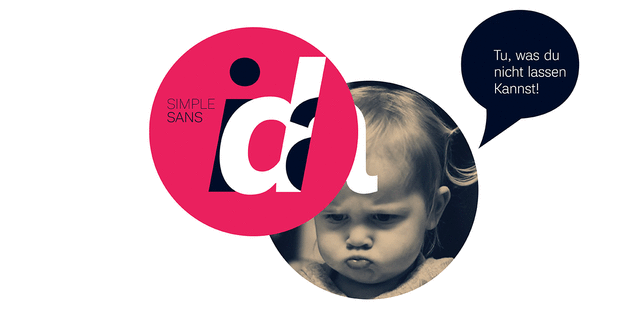
Шрифт Ida обладает простотой и утилитарностью гротесков конца XIX–первой половины XX века и тёплым, дружелюбным характером. Закрытые формы и низкий контраст штрихов в сочетании с изяществом скелета знаков производят впечатление одновременно рациональности и уюта. Эмоционально шрифт похож на ламповый приёмник, однако по составу и функционалу является абсолютно современным. В Ida 18 начертаний — шесть прямых разной насыщенности, соответствующие им курсивы и зауженные начертания. Знаковый состав дополнительно включает альтернативные формы некоторых знаков, капитель и индексные цифры. Шрифт подготовлен Марией Харламовой (Селезеневой) и выпущен компанией ПараТайп в 2017 году.
11-е из 18 начертаний
Функции начертания Ida BoldПрименение в макете:
Ассоциации c начертанием Ida BoldКачества и характер:
убедительный, серьезный, строгий, спокойный, универсальный, понятный, простой, деловой, уравновешенный, умеренный, практичный, доступный, устойчивый, мотивирующий, ответственный, твердый, качественный, добротный, традиционный, консервативный, старомодный, статичный, дружелюбный